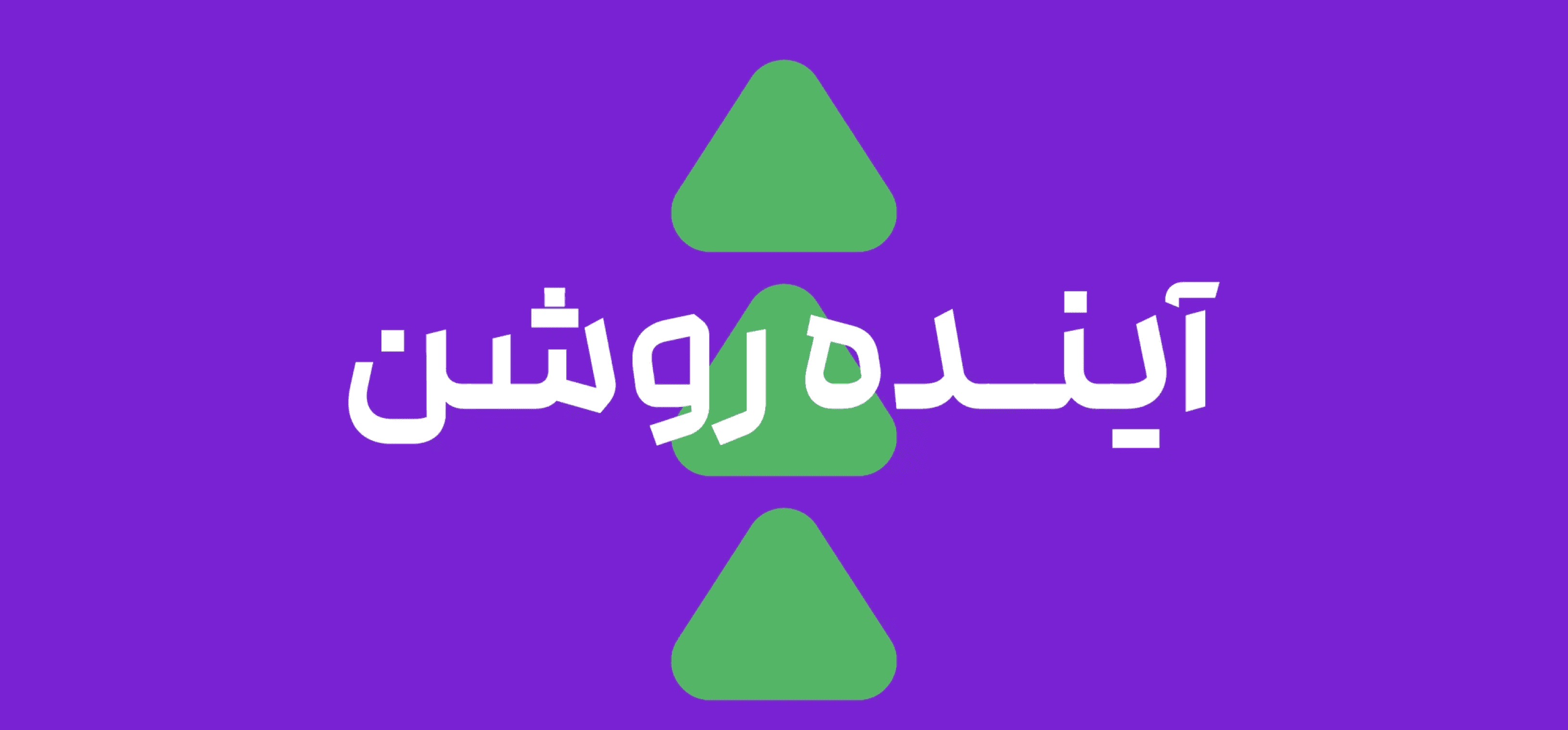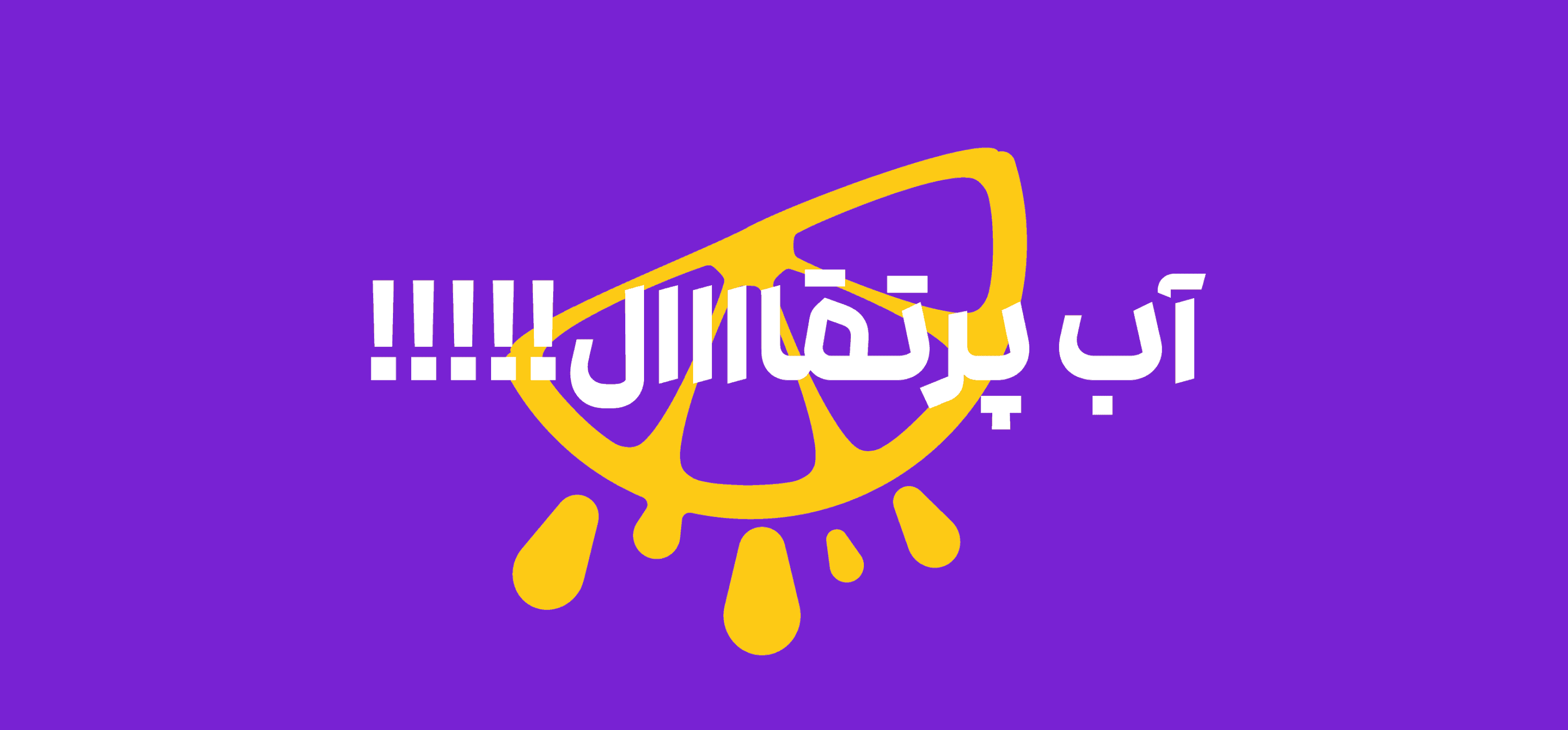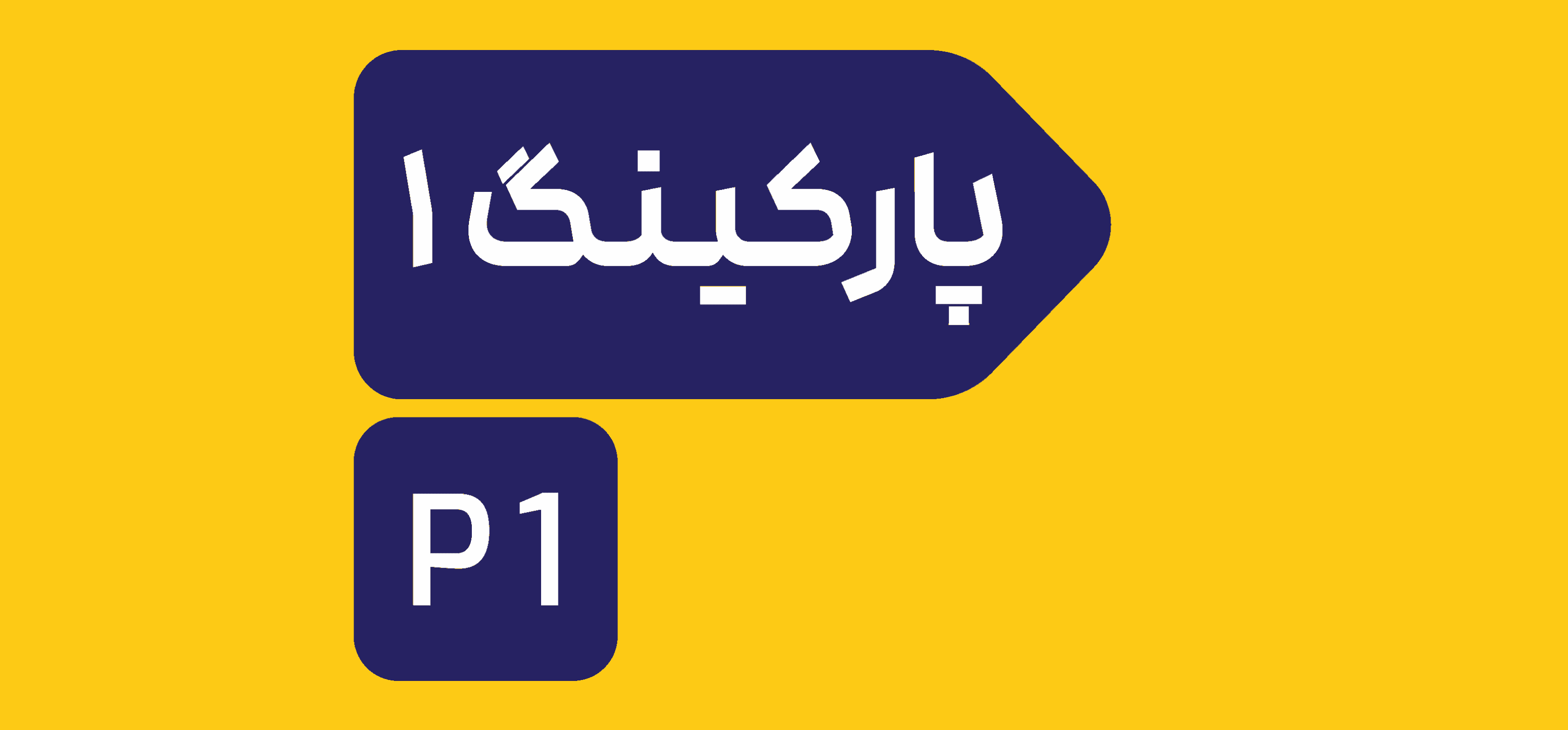
خط رخ صُمم ليُظهر جماله ويتباهى بحضوره البصري اللافت. تصميم الحروف المميز في هذا الخط يمنح كل نص مظهرًا جديدًا وفريدًا.
ينتمي رخ إلى فئة الخطوط الهندسية، ورغم طابعه العرضي والزخرفي العالي، فإنه يحافظ على وضوح جيد في النصوص القصيرة، مما يجعله خيارًا مثاليًا للعناوين والتصميمات التي تتطلب لفت الانتباه.
خط رخ صُمم ليُظهر جماله ويتباهى بحضوره البصري اللافت. تصميم الحروف المميز في هذا الخط يمنح كل نص مظهرًا جديدًا وفريدًا.
ينتمي رخ إلى فئة الخطوط الهندسية، ورغم طابعه العرضي والزخرفي العالي، فإنه يحافظ على وضوح جيد في النصوص القصيرة، مما يجعله خيارًا مثاليًا للعناوين والتصميمات التي تتطلب لفت الانتباه.
خط رخ صُمم ليُظهر جماله ويتباهى بحضوره البصري اللافت. تصميم الحروف المميز في هذا الخط يمنح كل نص مظهرًا جديدًا وفريدًا.
ينتمي رخ إلى فئة الخطوط الهندسية، ورغم طابعه العرضي والزخرفي العالي، فإنه يحافظ على وضوح جيد في النصوص القصيرة، مما يجعله خيارًا مثاليًا للعناوين والتصميمات التي تتطلب لفت الانتباه.